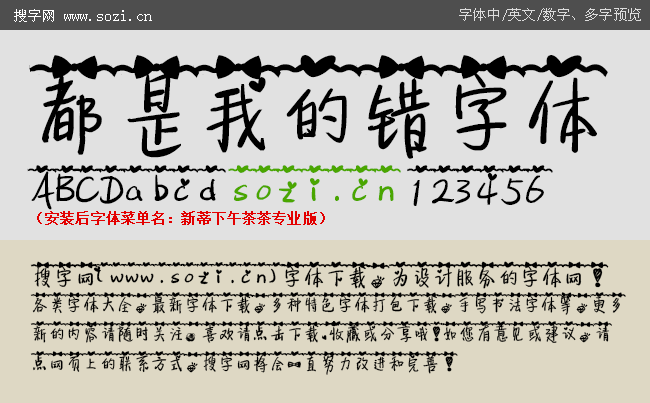
都是我的錯(cuò)字體
搜字網(wǎng)給大家提供一款書(shū)法風(fēng)格的手機(jī)中文字體下載。修改者給他起名為都是我的錯(cuò)字體,這款手機(jī)字體是以新蒂下午茶字體為原形,給字體加上了可愛(ài)的卡通花邊,連標(biāo)點(diǎn)也替換成了卡通圖案,新蒂下午茶字體是一款手寫(xiě)風(fēng)格的中文簡(jiǎn)體字體,非常有手寫(xiě)感,加入花邊后更加可愛(ài),喜歡的朋友可下載收藏。